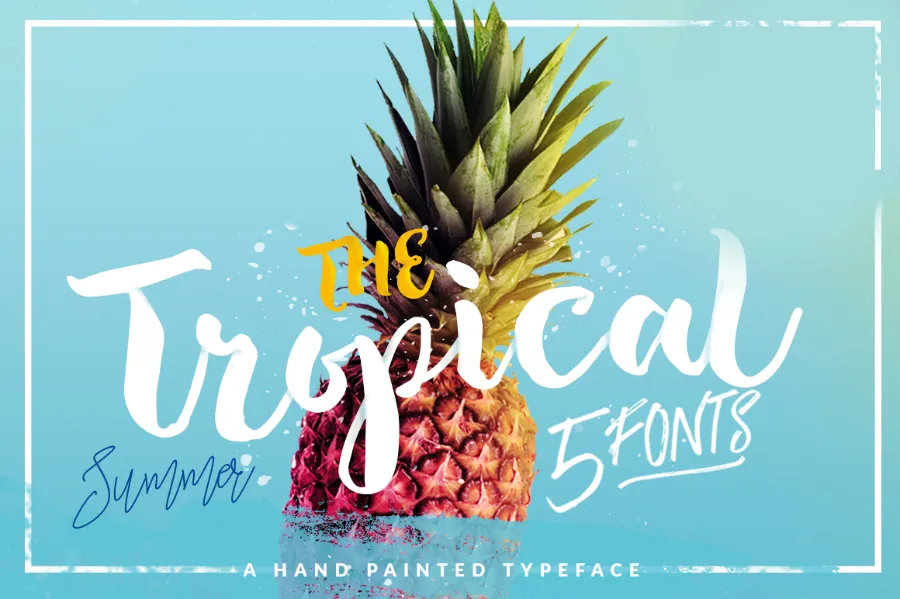
Sente-se à beira do oceano caribenho quando descobre The Tropical Script Font, uma paixanteira escolha para os criadores de designs digitais. Este conjunto cuidadosamente elaborado de fonts, concebidas para trabalharem em harmonia entre si, é perfeito para criar desenhos de tipos a mão que exalam vida e entusiasmo. Obrigatório por designers de capas de livros, revistas, roupas, cartões personalizados, logotipos, folhetos e até mesmo postais, esta fonte Brush está repleta de recursos Opentype para oferecer infinitas possibilidades ao designer. O design minimalista mas elegante da fonte realça qualquer conteúdo que seja acentuado por ela, criando um contraste atraente entre o texto e o fundo. Cada uma das cinco fontes The Tropical Script Font possui uma textura única e colorida, capaz de criar uma atmosfera tropical vibrante para qualquer projeto. Seja você um designer gráfico atemporal ou alguém em busca da sua própria identidade visual, esta fonte é perfeitamente adaptável aos mais variados estilos e formatos. A Hamilton é o autor responsável pelo design destas maravilhosas fonts, oferecendo um conjunto de ferramentas para os designers com uma paixão por criar designs coloridos e animados. Obrigado a todos que já experimentaram The Tropical Script Font e amam seu resultado impecável – agora é a sua vez de criar algo único!